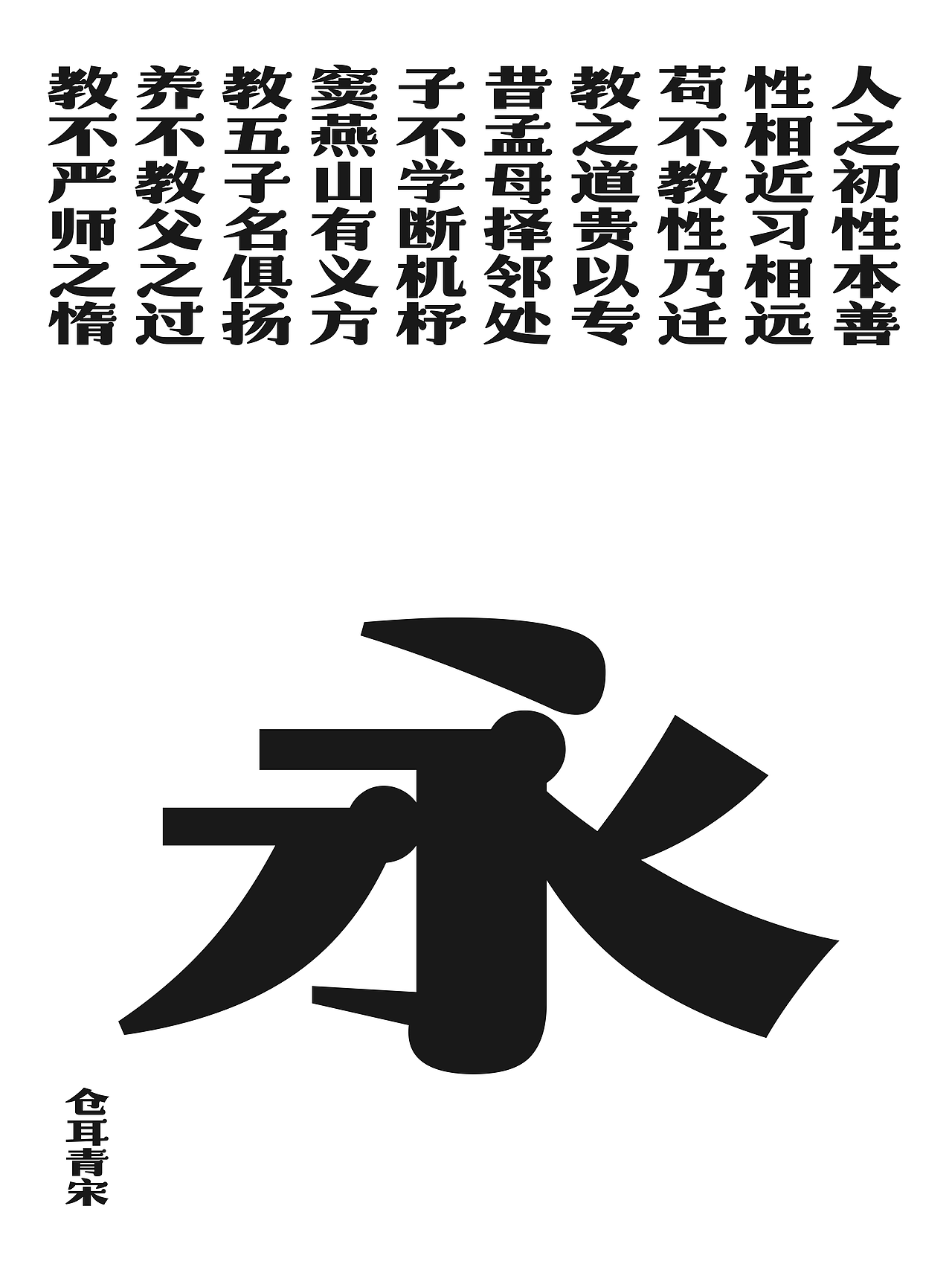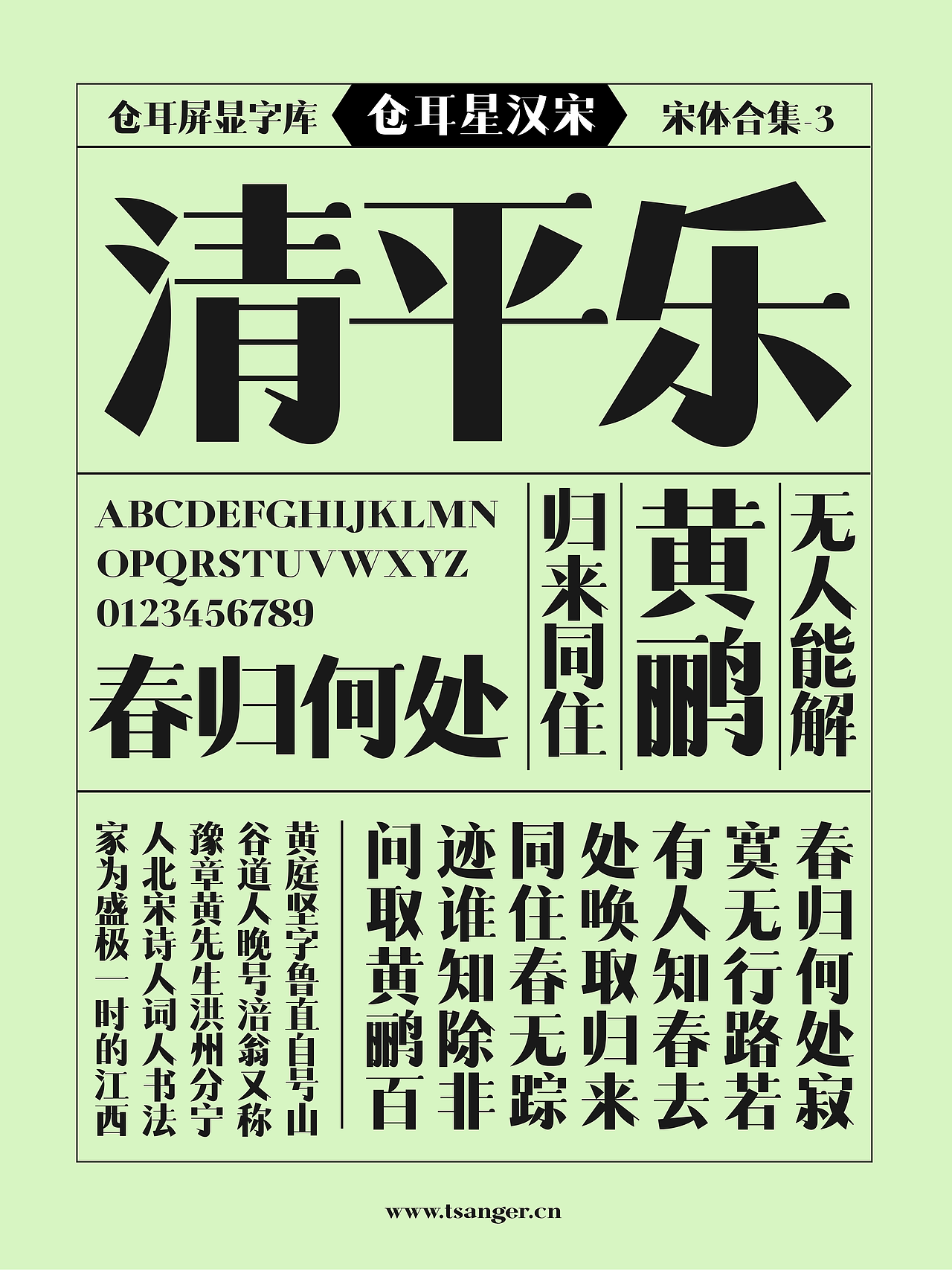
宝藏宋体合集推荐
今天为大家分享一下仓耳屏显字库推出的多款宋体字库,形式多样,适用于多种应用场景,如用于海报、品牌广告、企业logo、品牌字、图书封面、产品包装设计等。
仓耳雅宋:笔画简洁利落,圆融柔和,用圆头消减传统宋体的锋利,增加了亲切感与科技感,适用于标题、牌匾、对联、海报、广告、图书封面、包装设计等。
仓耳青宋:字体结构稳重,端庄匀整,字里行间蕴含着书法的气韵。造型趋扁,笔形饱满,整体风格雄厚醒目,适合用于标题、牌匾、对联、大型海报、品牌广告、图书封面、散文诗集、产品包装设计和节日广告等。
仓耳星汉宋:从美术字中获取的灵感,笔画紧凑,结构上紧下松,符合书法的审美特点。笔画均衡,疏密得当,简洁的笔形和横竖极强的粗细对比使其显现出摩登时尚的字形特点。
仓耳聚珍长仿源自中华书局聚珍仿宋铅字样本,在原有的繁体基础上增补了简体,包含简繁双体。这款字体字型修长,布局匀称,笔画清秀。适合用于正文、海报、品牌广告、图书封面、散文诗集、产品包装设计等。